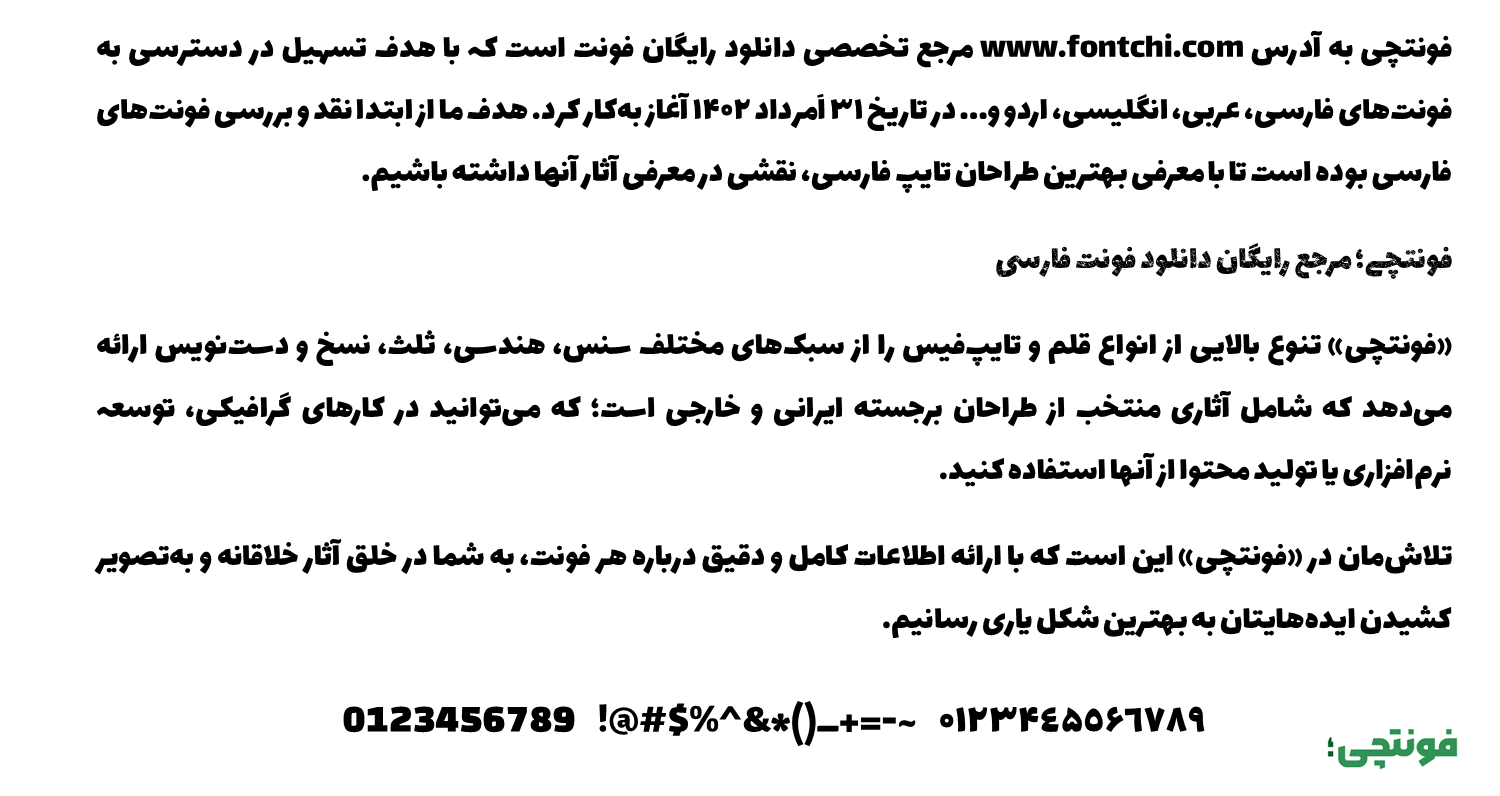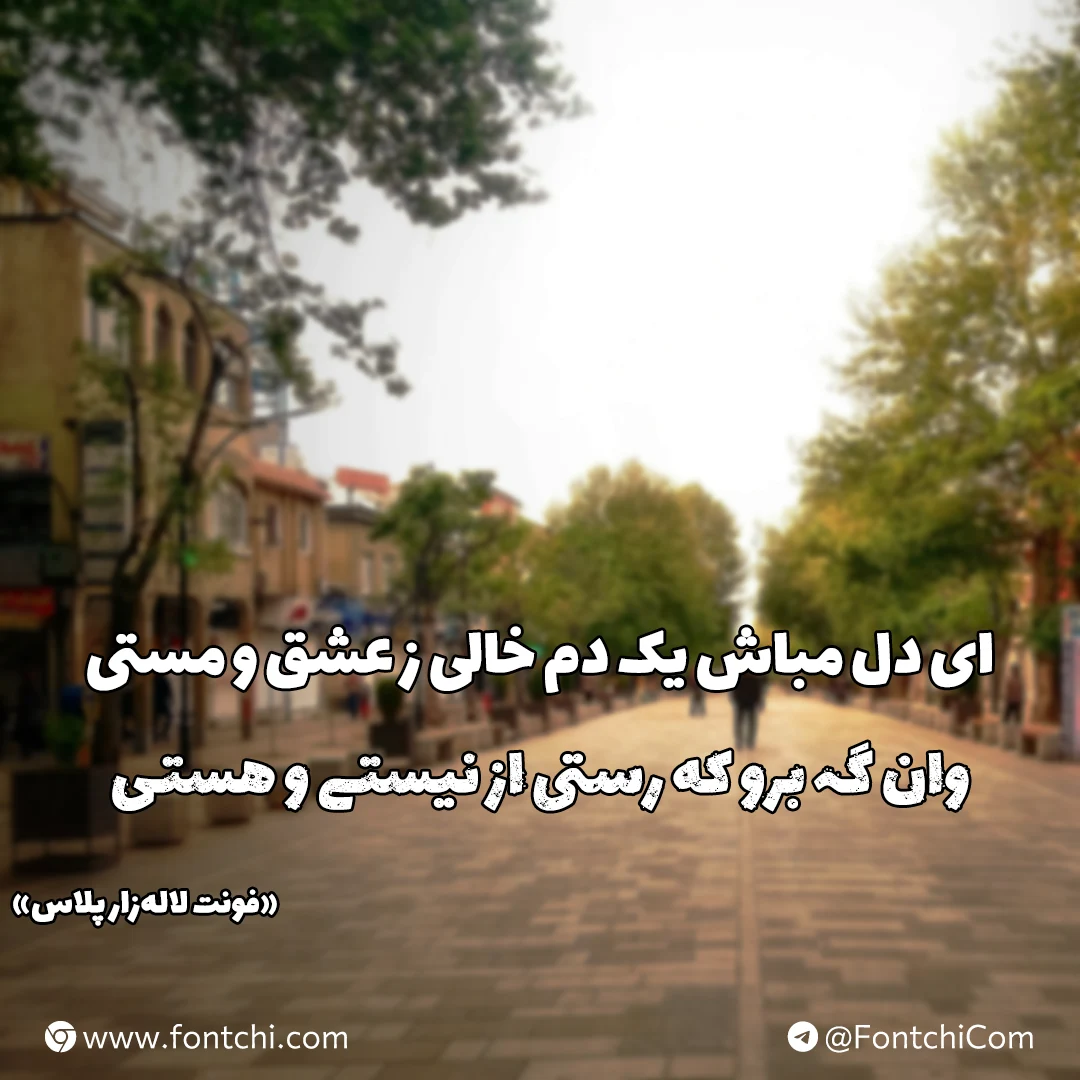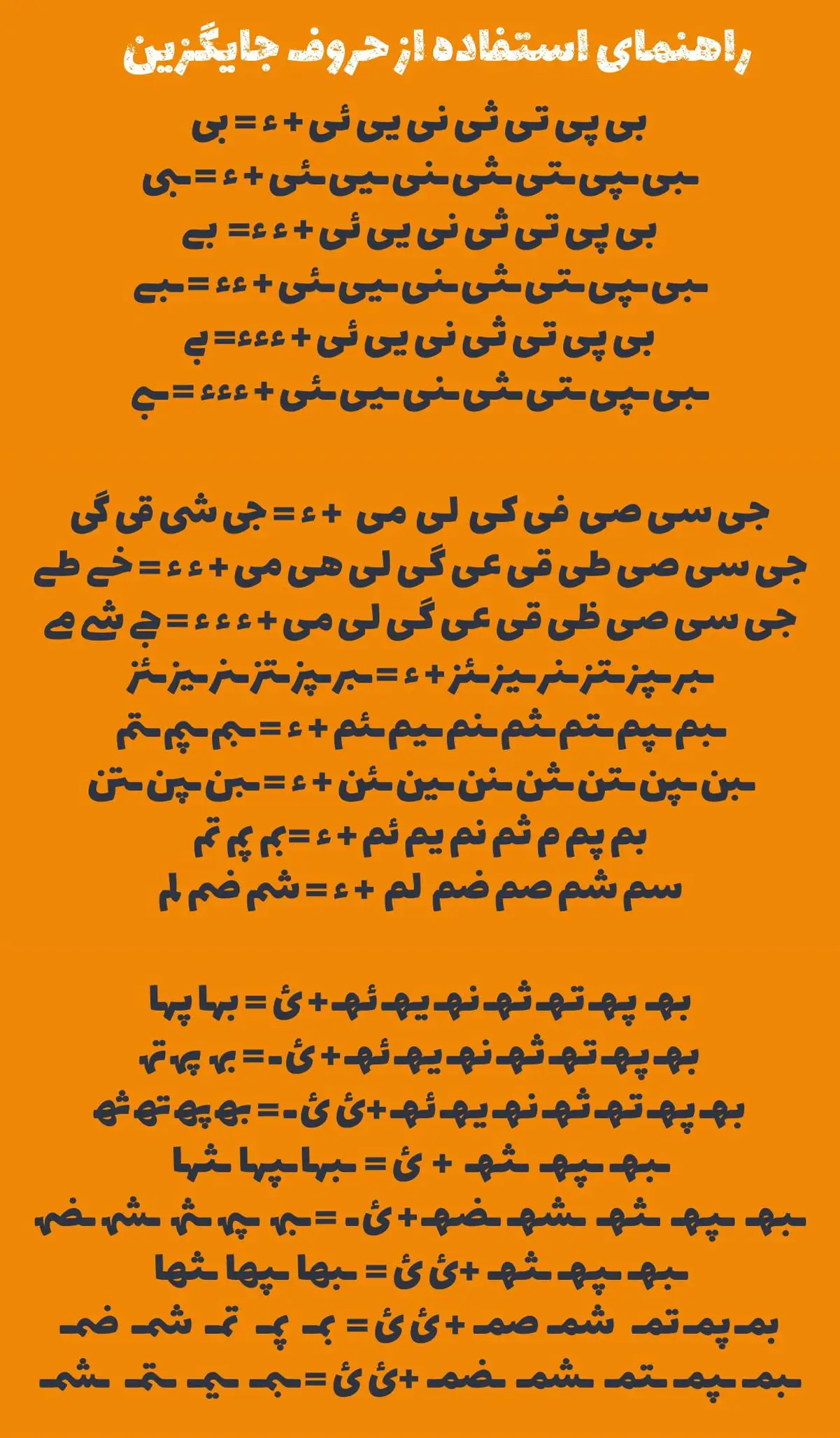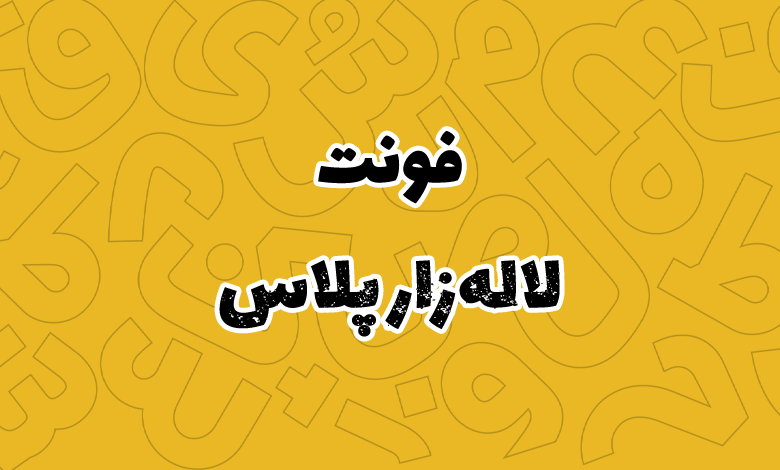
فونت لاله زار پلاس (Digi Lalezar Plus)
فونت لاله زار پلاس یا دیجی لاله زار پلاس (به انگلیسی: Digi Lalezar Plus) از سری فونتهای اصلاح شده فارسی است که نسخهای بهبود یافته از فونت لاله زار معمولی است. در این فونت جدای از اضافه شدن ۳ استایل مختلف برای فونت که شامل نقطه گرد، معمولی و سنگی است، پشتیبانی از حروف و ترکیبات جایگزین متعدد انجام گرفته است.
طراح فونت لاله زار پلاس مهدی برقگیر است که این فونت را به صورت رایگان عرضه کرده است. میتوانید از آن در عناوین و متون کوتاه که نیاز به فونتی نمایشی دارید استفاده کنید. پشتیبانی از حروف جایگزین آن را به گزینه خوبی برای تبلیغات و متونی که نیاز به جلب توجه دارند تبدیل کرده است. در ادامه به بررسی این فونت رایگان فارسی میپردازیم.
بررسی و دانلود فونت لاله زار پلاس رایگان (Digi Lalezar Plus)
فونت لاله زار پلاس که الهام گرفته از سبک حروفنگاری پوسترهای سینمایی دهههای ۴۰ و ۵۰ شمسی است، با افزودن استایلهای متنوع و ویژگیهای مدرن، به یکی از گزینههای محبوب برای طراحیهای نمایشی و تیتر تبدیل شده است.
فونت لاله زار اصلی در سال ۱۳۹۴ توسط برنا ایزدپناه و با حمایت شرکت گوگل به صورت رایگان منتشر شد. سپس مهدی برقگیر با هدف بهبود این فونت و رفع برخی محدودیتهای نسخه اصلی، مانند کمبود حروف جایگزین و مشکلات اعرابگذاری، نسخه لاله زار پلاس را توسعه داد. این نسخه با حفظ اصالت فونت اصلی، ویژگیهای جدیدی مانند استایلهای متنوع (مانند گرانج و نقطهگرد) و حروف جایگزین متعدد را ارائه کرده تا پاسخگوی نیازهای طراحان مدرن باشد.
لاله زار پلاس یک فونت نمایشی با وزن سنگین (Extra Bold) است که برای تیترها و عناوین طراحی شده و حس نوستالژیک پوسترهای سینمایی را با ظاهری مدرن ترکیب میکند. این فونت در سه استایل مختلف عرضه شده است:
- استاندارد که شامل نسخه عادی با نقطهگذاری مربعی است.
- نقطهگرد که سبک نقطهها در آن تغییر کرده است.
- گرانج که دارای حالت گرافیکی سنگی مانند است و برای کارهای نمایشی مناسب است.
هر سه سبکهای فونت لاله زار پلاس از زبانهای فارسی، عربی، کوردی، اردو و انگلیسی پشتیبانی کاملی دارند. بهطوریکه در بخش اعداد نیز شاهد استفاده از گلیفهای استاندارد هر زبان هستیم.
خوانایی بالای فونت در اندازههای بزرگ، آن را برای پوسترها، بنرها و محتوای شبکههای اجتماعی ایدهآل میکند. خصوصا برای استفاده در تامنیل ویدئو کانال یوتوب که میتواند روی افزایش نرخ کلیک موثر باشد.
راهنمای حروف جایگزین فونت دیجی لاله زار پلاس
یکی از مهمترین تفاوتهای فونت لاله زار پلاس نسبت به نسخه اصلی، پشتیبانی از حروف و ترکیبات جایگزین در همه سبکهای این فونت است. در این فونت میتوانید حروف و ترکیباتی مانند «ی، س، ش، ه، م، ـر، ـز، ـژ، ـن» را مطابق تصویر زیر در حالتهای مختلفی تایپ کنید.
کافی است مانند تصویر زیر از کاراکترهای «ء» یا «ئ» استفاده کنید تا حروف و ترکیبات مانند بالا با ظاهر متفاوتی تایپ شوند.